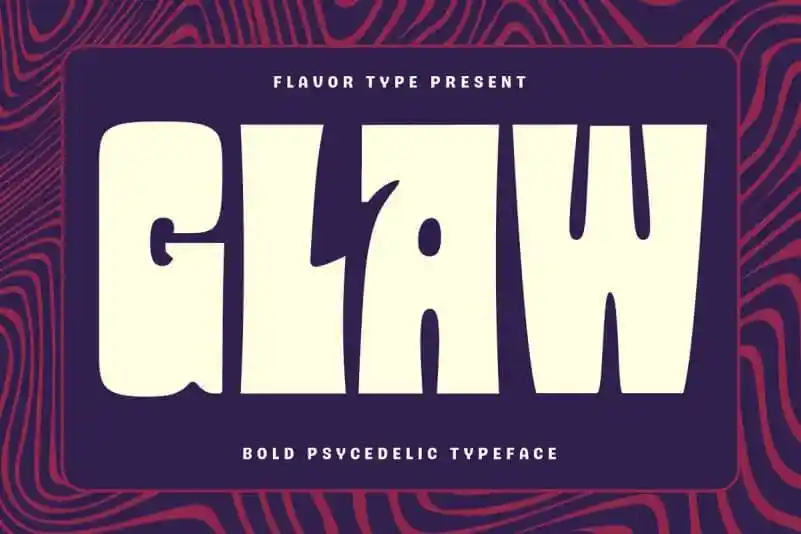
Glaw Display Font é uma elegante tipografia criada para ambientes visuais que exigem destaque e impacto, perfazendo-se em influências vintage inspiradas nos títulos coloridos dos anúncios de entretenimento Hanna-Barbera dos anos 50 a 70. Com um design bold e poderoso, Glaw apresenta toda a alfabetização do A ao Z, uma combinação completa de números e símbolos adicionais que tornam essa fonte perfeita para qualquer aplicação visual exigente. Além disso, o designer Ilham Herry desenvolveu Glaw com um novo enfoque, incorporando ideias da década de 1970, do psicodélico ao funk, hippie e festas. Embora a inspiração seja claramente nesse tema, Glaw também oferece flexibilidade para que os designers possam criar novos estilos ou temas sem perder o brilho inconfundível da Psychedelic Style. Seu design inclui três pesos (light, regular e bold) em OTF formatado de forma tradicional, condensado e ampliado, atraindo um público amplo. Para aqueles que possuem software compatíveis com fonts variáveis como o Adobe Illustrator ou Photoshop, Glaw oferece um rótulo extra: 100 peso, garantindo assim uma variedade infinita de opções para personalizar suas criações em qualquer plataforma ou formato.